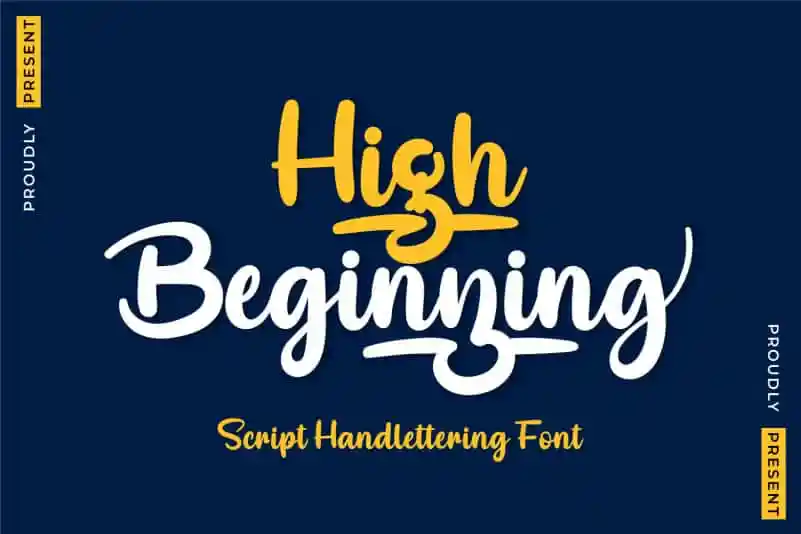
High Beginning Script Font – Download Grátis
A High Beginning Script Font é uma nova adição à nossa gama de fuentes script, oferecendo um estilo moderno e artístico que se destaca entre as demais. Cada letra na fonte tem uma forte expressão e beleza, perfeita para uso em títulos ou frases para criar um efeito elegante em suas criações gráficas. Esta fonte é ideal tanto para designers profissionais quanto para amantes do design que buscam dar um toque único a seus projetos visuais. A High Beginning Script Font é mais do que uma fonte; ela é um complemento perfeito para qualquer projeto, seja ele um site, um banner ou até mesmo uma capa de livro, onde o equilíbrio entre modernidade e originalidade faz toda a diferença.